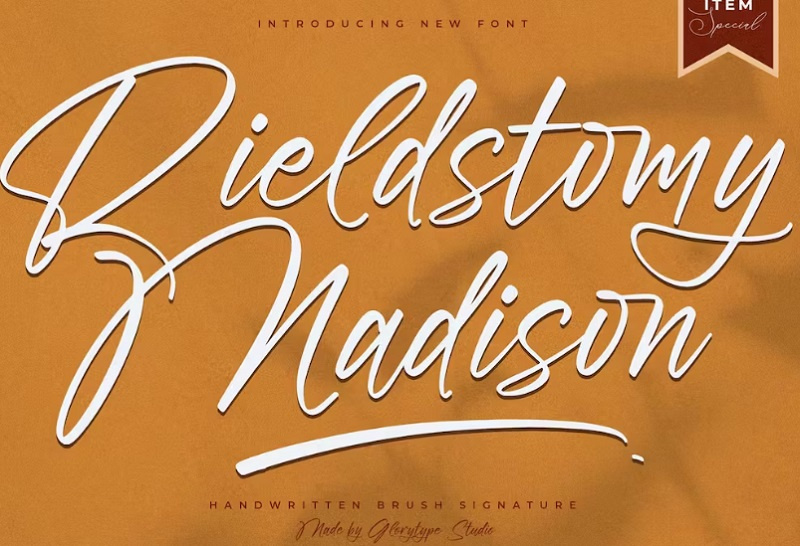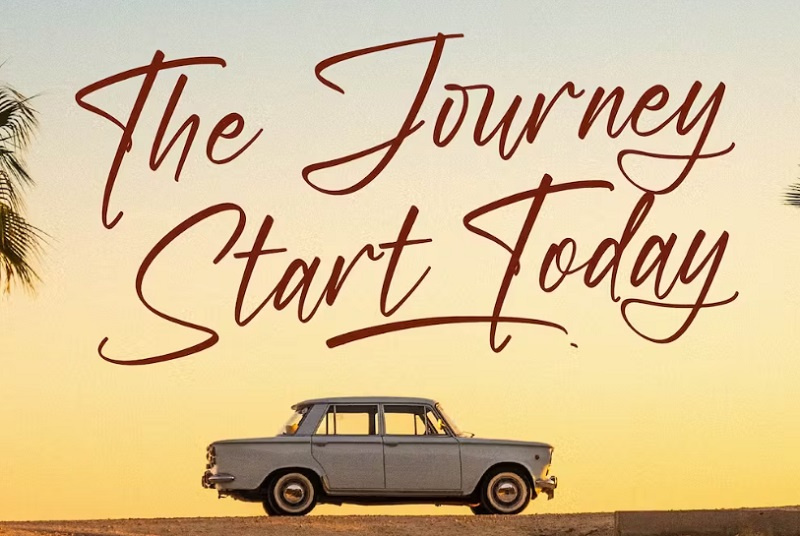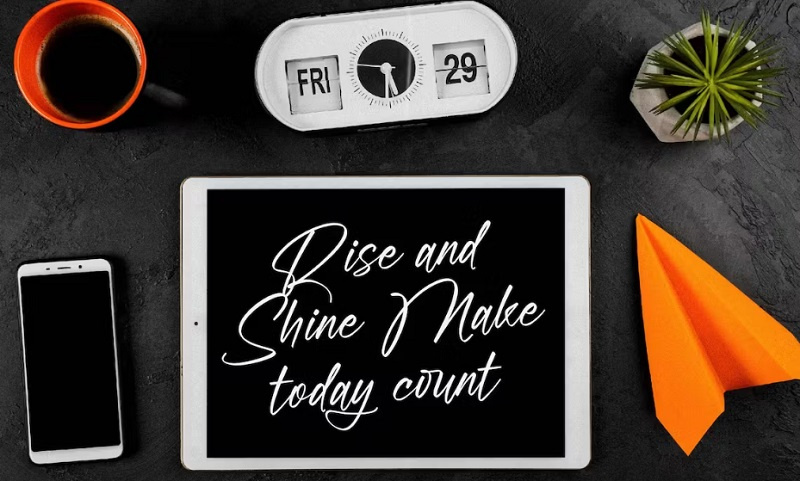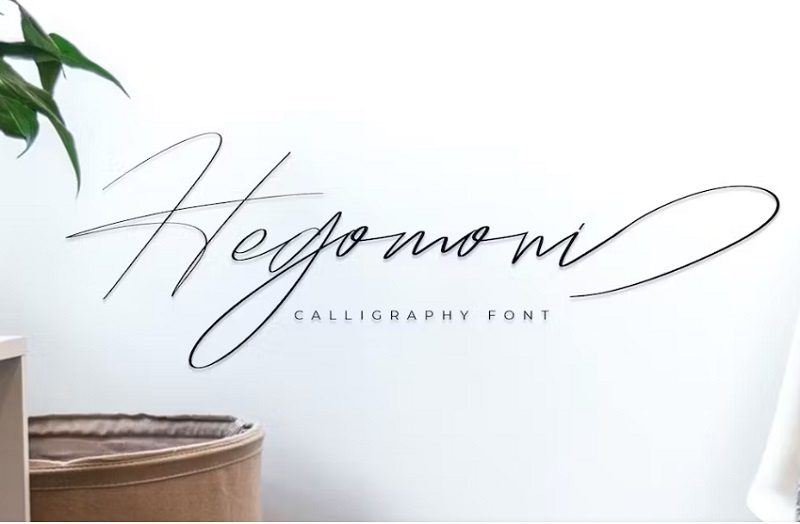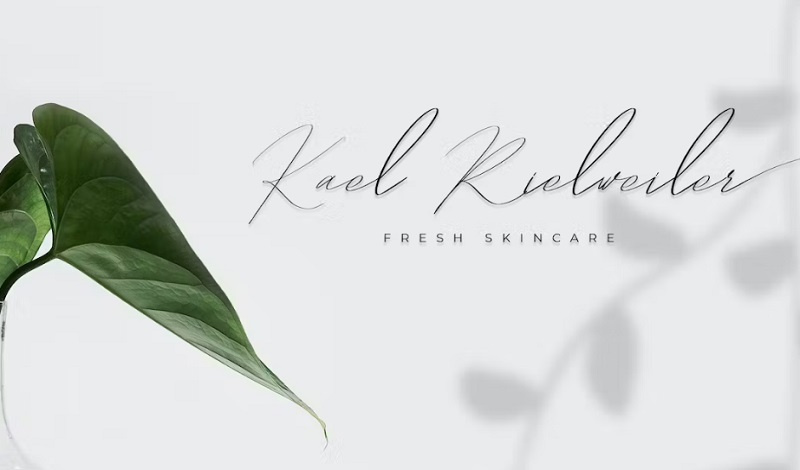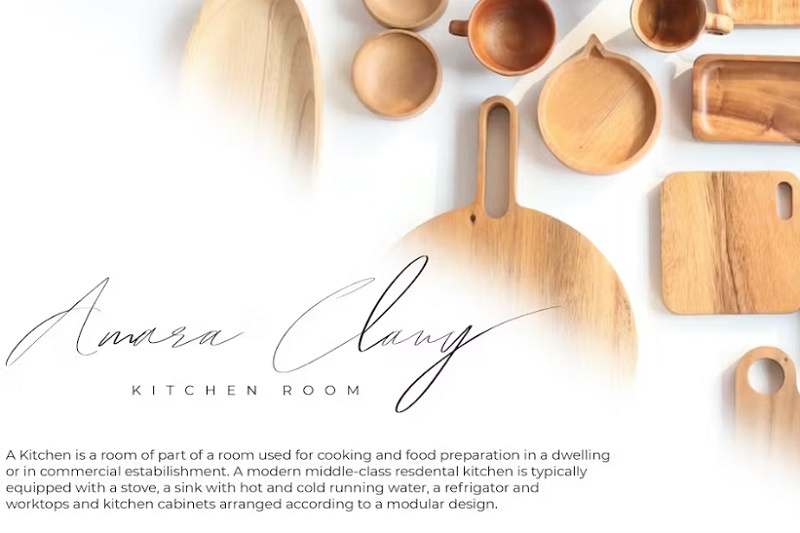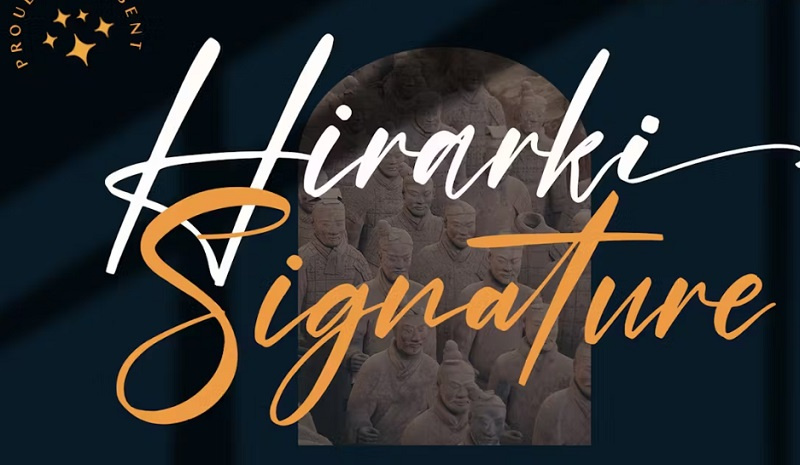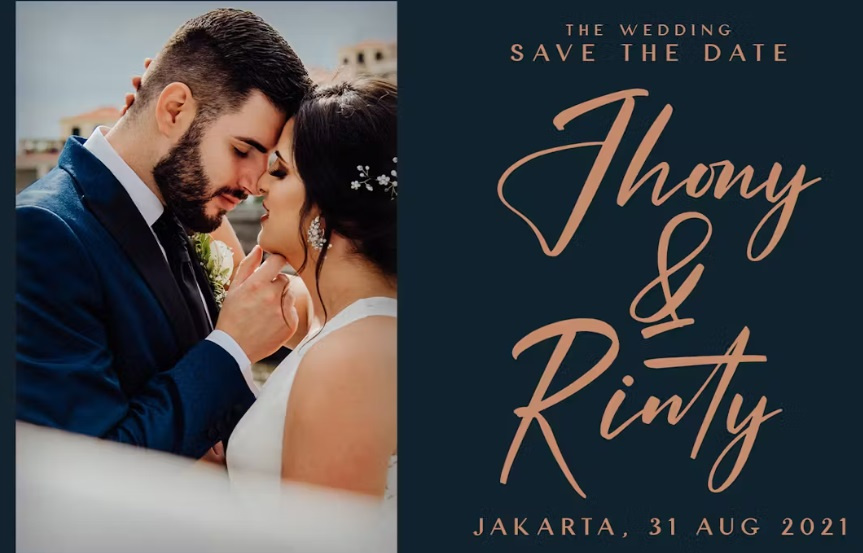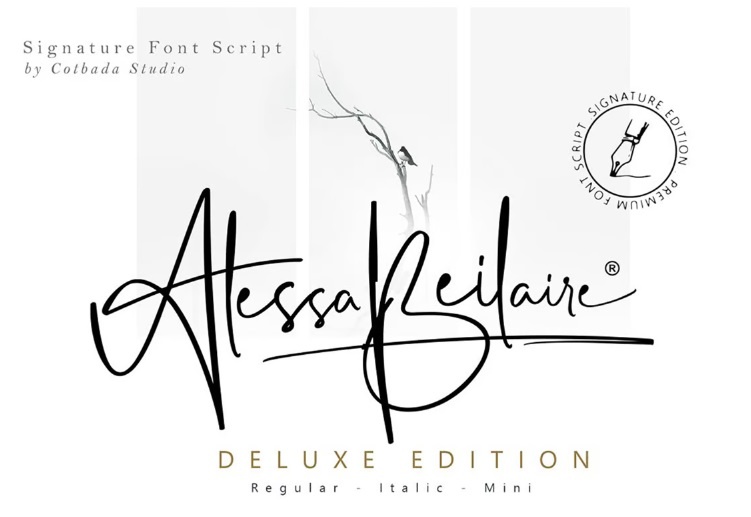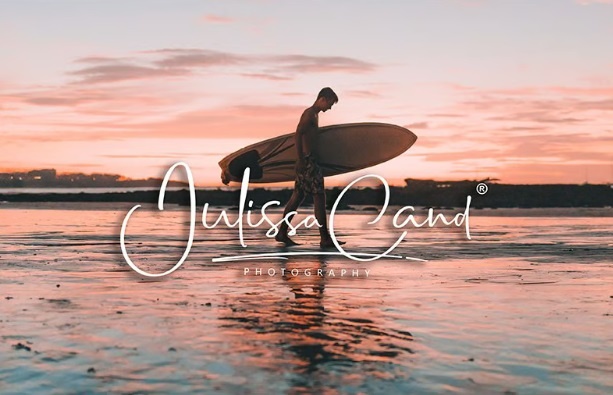
فونت انگلیسی امضا⭐8 فونت انگلیسی طرح امضا Lattravis Signature
فونت انگلیسی امضا دارای 7 فونت زیبا با سبک فونت مدرن و با کلاس است. این فونت انگلیسی طرح امضا مناسب انواع طراحی ها برای لوگوها، نام های تجاری، نقل قول ها، پوسترها، امضاها، برچسب ها، طراحی بسته بندی، سرفصل های وبلاگ، پادکست ها و غیره است. فونت انگلیسی امضایی با طرح های متنوع می باشد که با فرمت های OTF و TTF بر روی سایت برای دانلود قرار داده شده است.
2- دانلود فونت امضاء انگلیسی Perfect Signature
در این بخش با معرفی یک فونت انگلیسی به سبک امضا با نام Perfect Signature با شما همراه هستیم. یک فونت دستنویس جذاب به پروژههای شما می دهد. این فونت امضاء انگلیسی مناسب برای برندسازی، آلبوم موسیقی، لوگو یا هر پروژه خلاقانه لوکس و با کلاس می باشد. شامل فایل های TTF، OTF، WOFF و پشتیبانی از چند زبانه.
3- فونت انگلیسی سبک امضا
این فونت انگلیسی سبک امضا در سه فایل WOFF، TTF، و OTF موجود می باشد. این فونت انگلیسی برای ساخت امضا مناسب برای طراحان می باشد. از این فونت می توانید برای تایپوگرافی، طراحی های گرافیکی و تبلیغاتی استفاده نمایید.
4- فونت انگلیسی طرح امضا
Hegomoni Signature یک فونت طرح امضا است که می توانید از آن برای ایجاد یک طرح استفاده کنید. از آن برای برندسازی، لوگوها، مجلات، عنوان کتاب، کارت ویزیت، طرح های زیبای مد، تبلیغات، طرح های محصول، دعوت نامه عروسی، امضا یا نقل قول دست نویس استفاده نمایید.
فونت انگلیسی امضا برای اینشات
Hirarki Signature یک فونت اسکریپت با حروف نازک و ظریف است. از این فونت انگلیسی امضا برای اینشات برای ایجاد طرح های زیبا استفاده کنید. این فونت دارای کد PUA است که به این معنی است که شما می توانید به راحتی به تمام حروف دسترسی داشته باشید! با فرمت های ttf/otf ارائه شده است.
دانلود فونت انگلیسی به سبک امضا alessa beilaire deluxe
alessa beilaire deluxe یک فونت انگلیسی به سبک امضا و بسیار پرطرفدار است. این فونت گزینه عالی برای ایجاد واترمارک در عکاسی، طراحی لوگوی امضا، جلد آلبوم، کارت ویزیت و بسیاری از پروژه های طراحی دیگر است.
فونت امضا انگلیسی برای اینشات
Tyloos نام این فونت امضا انگلیسی برای اینشات می باشد. این فونت دستنویس با خط شکسته، مناسب برای لوگو، بسته بندی محصول، عناوین بازی، عنوان کتاب/ جلد، پوستر فیلم، تصویر و موارد دیگر عالی است. فونت انگلیسی امضا شامل فایل های .otf/.ttf/.woff می باشد.